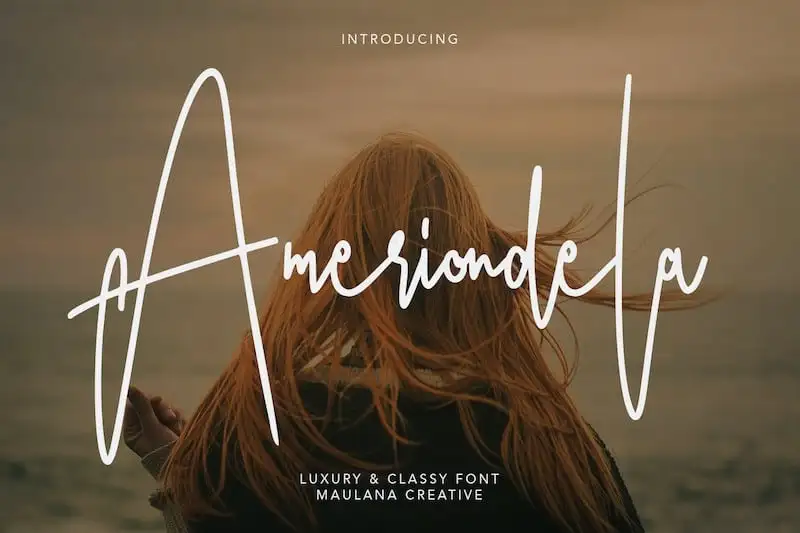
Ameriondela Handwritten Font – Download Grátis
Ameriondela é uma elegante e autêntica fonte escrita a mão que se destaca para quem busca um toque sofisticado em designs digitais. Desenhada pelo Maulana Creative, esta fonte é perfeitamente adaptável para diversas aplicações. Suas linhas delicadas e nuances humanizam qualquer layout, tornando-a uma escolha ideal para branding, cabeçalhos de mídia social, embalagens de produtos, convites de casamento e cartões personalizados. Ameriondela oferece um amplo conjunto de caracteres, incluindo letras maiúsculas e minúsculas básicas, números e pontuação. Com seu design meticuloso e características detalhadas, a fonte traz uma sensação elegante e artesanal ao seu projeto. Seja para criar marcações memoráveis ou cartões de convite com um toque autêntico, Ameriondela é perfeita para designers que buscam incorporar personalidade no design digital. Em uma era cada vez mais digitalizada, a fonte escrita a mão ainda oferece uma maneira única e eficaz de transmitir identidade visual. A elegância serena de Ameriondela permite aos profissionais de design criar designs autênticos que se destacam em qualquer formato digital ou impresso.